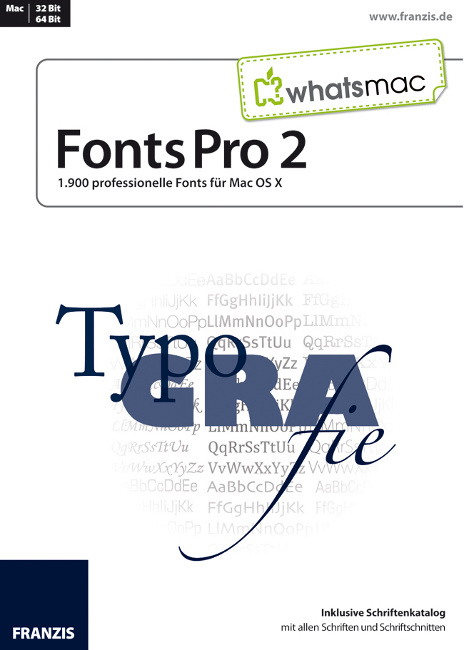
Fonts Pro 2
Mit Schrift gestalten
Lesbarkeit und schönes Layout sind die Grundlagen typografischer Gestaltung. Die gezielte und stilsichere Verwendung von Schriften unterstützt Ihr Layout in dessen Aussagekraft und verstärkt seine Wirkung.
Für die ganz individuelle Schriftgestaltung steht Ihnen ab sofort diese komplette Schriftenkollektion zur Verfügung.
Ob seriöses Bewerbungsschreiben, romantischer Liebesbrief oder verspielte Geburtstagseinladung - mit der passenden Schriftart perfektionieren Sie Ihre Schriftstücke. Setzen Sie kreative Akzente mit ausgefallenen Überschriften oder Schmuckinitialen.
Mit diesen exklusiven Fonts finden Sie ihren eigenen Stil.